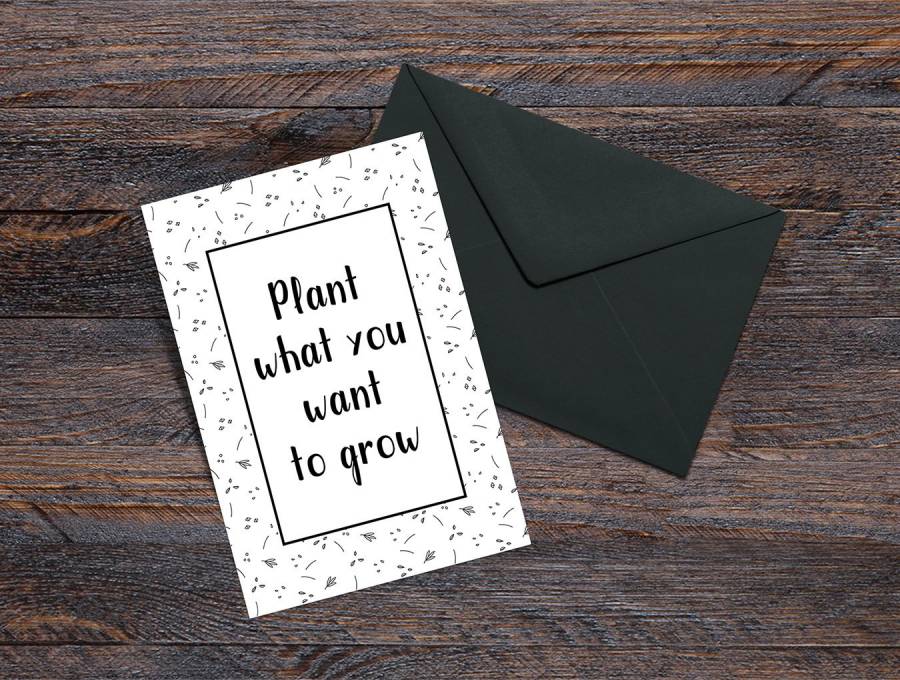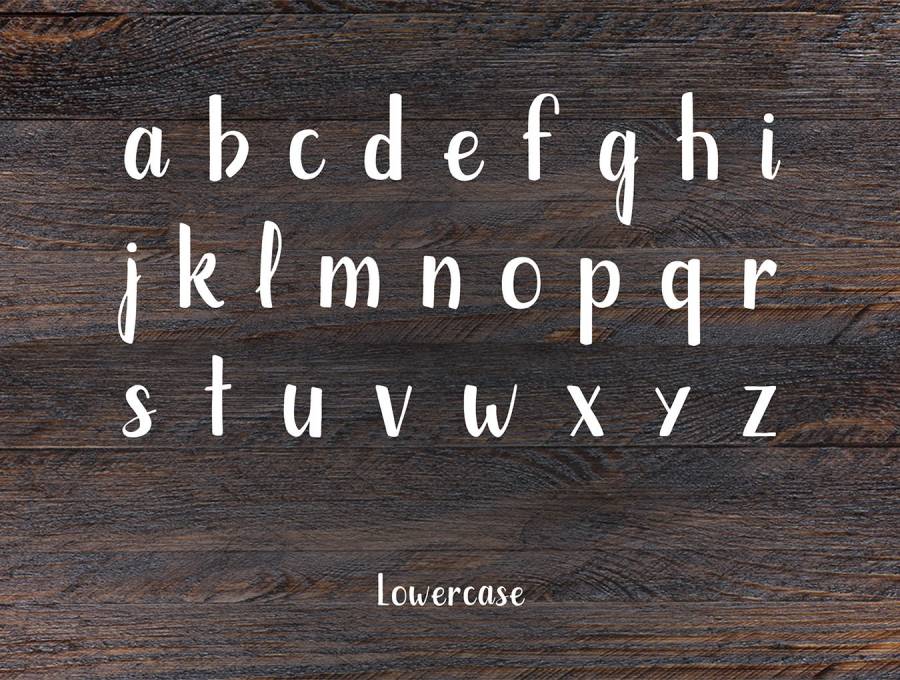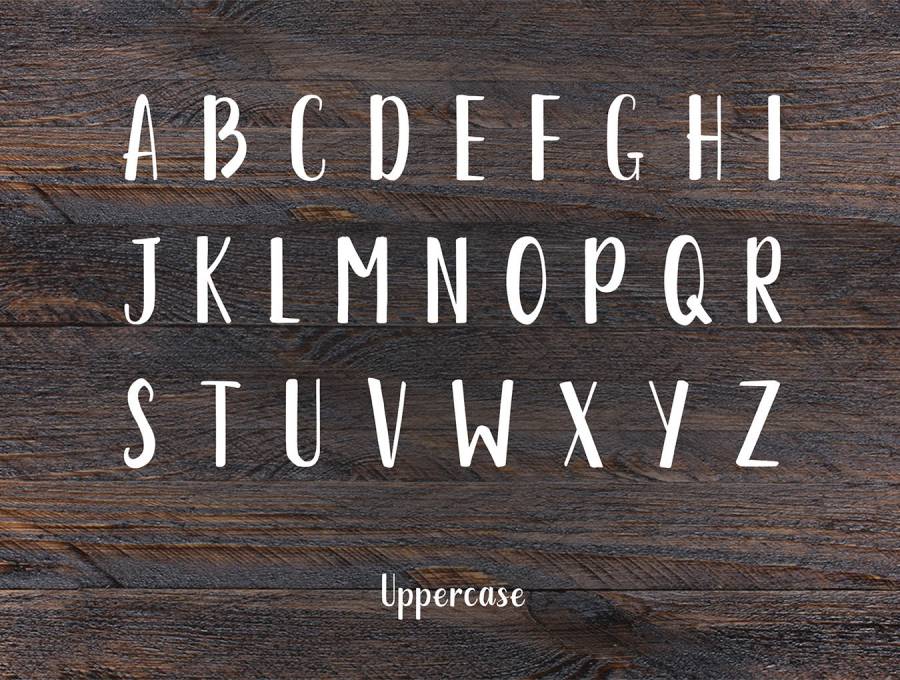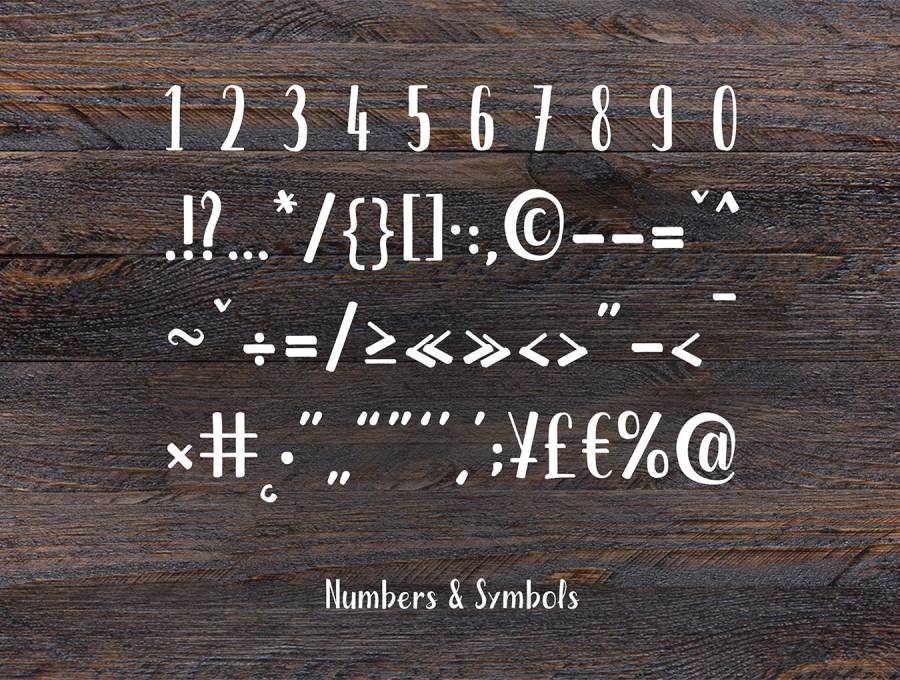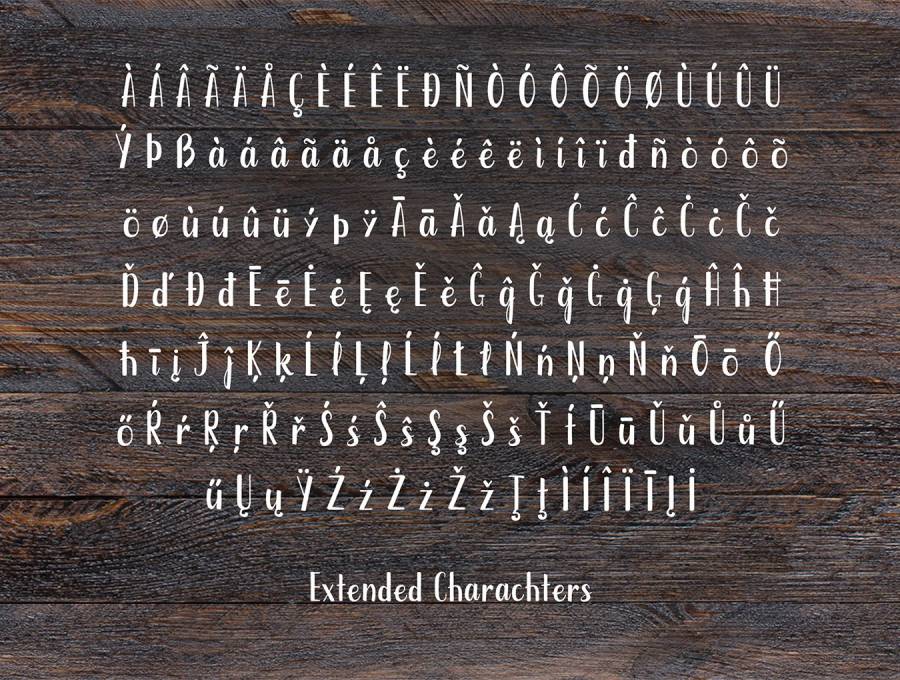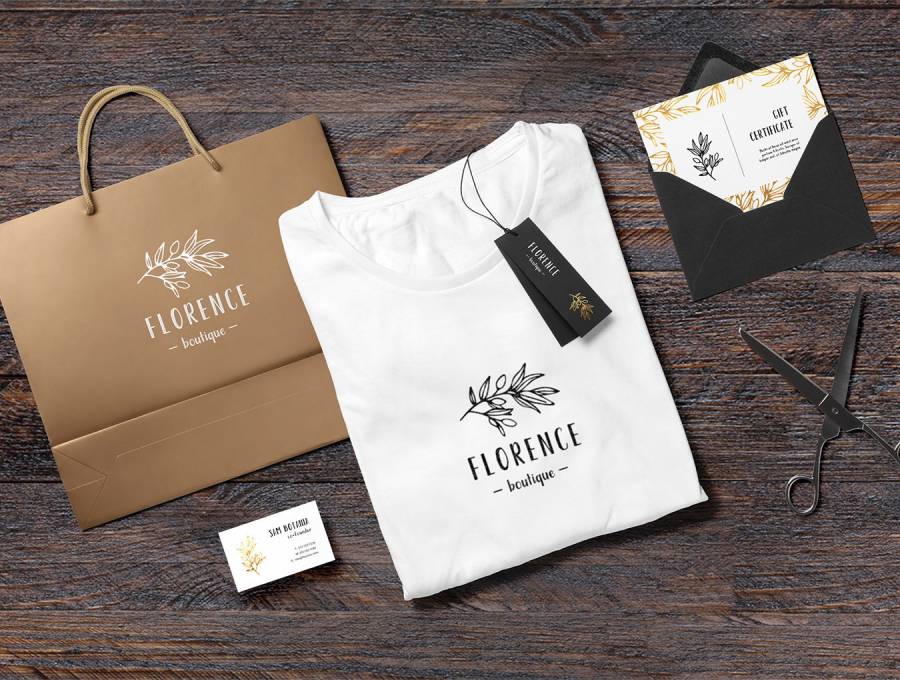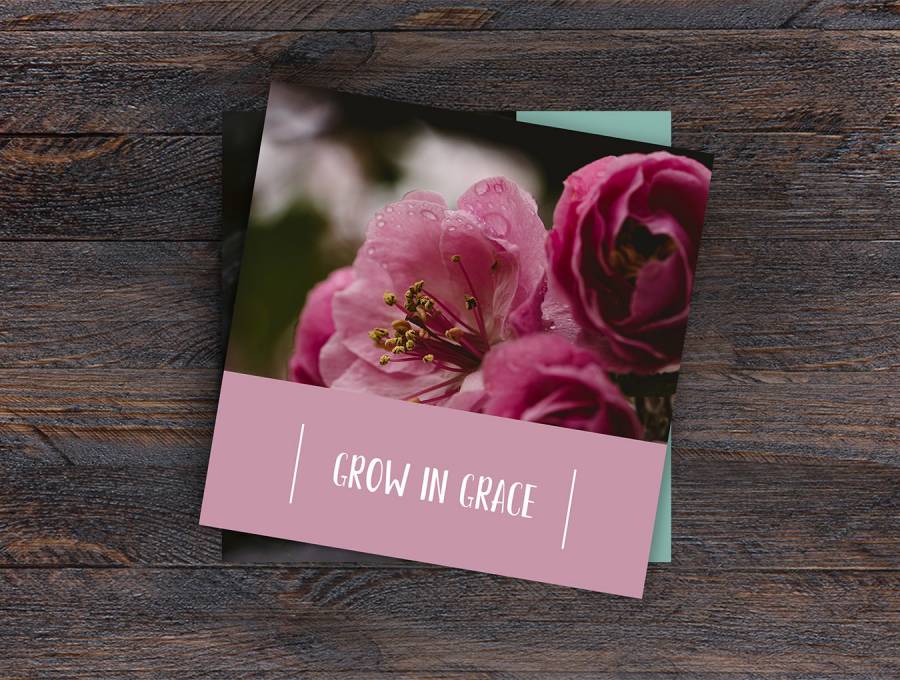
几何刷字体与下面的强大建筑。,Austra扩展刷字体
Geometric brush font with a strong construction underneath., Austra Extended Brush Font
Austra Extended Brush Font是一种几何画笔字体,下面有强大的结构。它适用于简短描述,徽标和品牌标识设计,包装,标题等。包括大写和小写字母,数字,符号和扩展字符。 你的WildOnes团队。